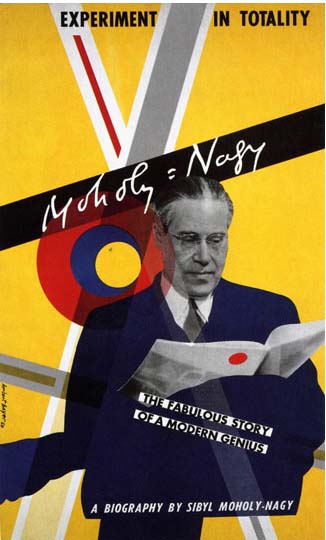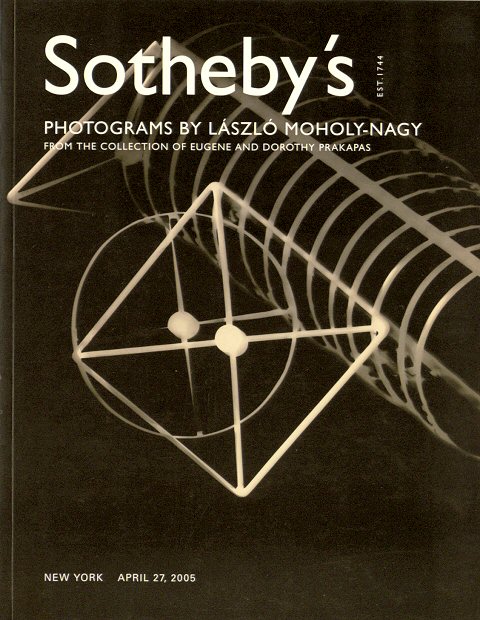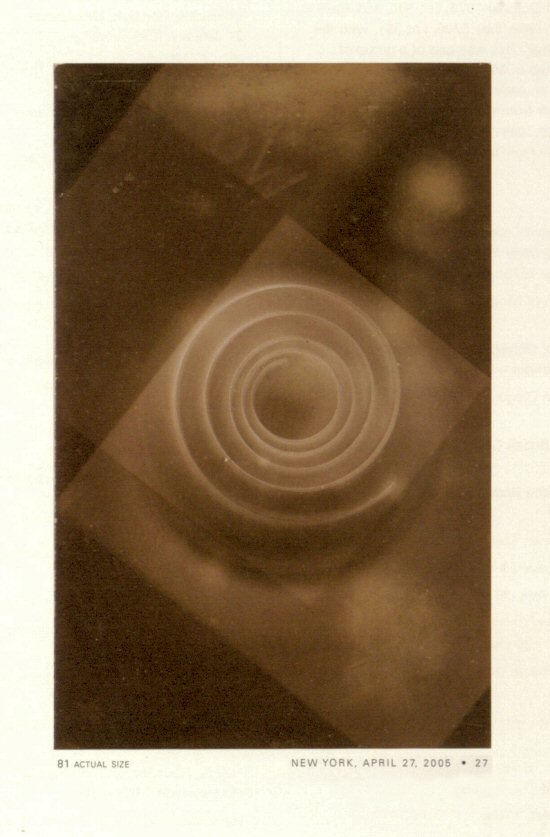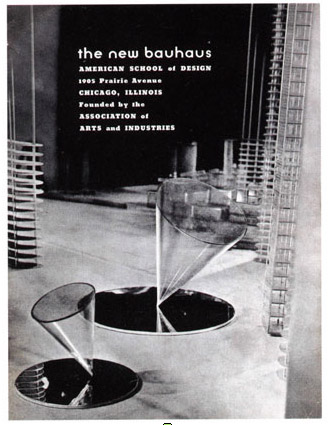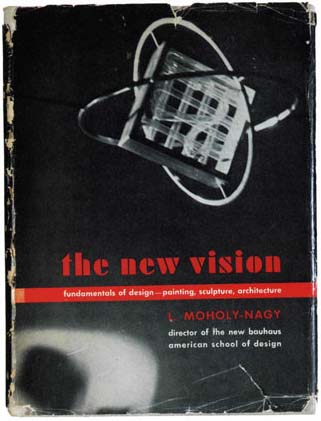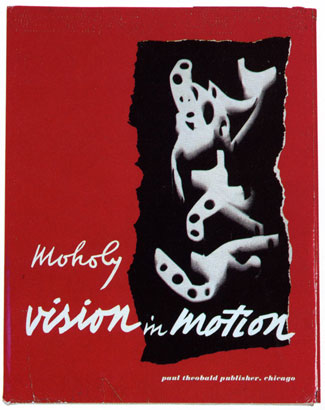
lászló moholy-nagy (1895 1946)Ensaísta, pintor, escultor, desenhador, fotógrafo e autor de fotomontagens, o húngaro Moholy-Nagy foi um verdadeiro «homem renascentista» do séc xx.
A criação de novas relações humanas e artísticas; a tradução da utopia em ação: são esses alguns dos princípios seguidos por Lázló Moholy-Nagy ao longo da sua vasta e diversificada obra.
László Moholy-Nagy (Bácsborsód, Hungria, 20 de Julho de 1895 Chicago, 24 de Novembro de 1946) foi designer, fotógrafo, pintor e professor de design pioneiro, conhecido por ter leccionado na Bauhaus. Foi influenciado pelo Construtivismo Russo e defendeu a integração da tecnologia e indústria no design e nas artes. Para László Moholy-Nagy não existiam divisões entre a fotografia, a pintura, a escultura e a arquitectura. A sua visão global foi fundamental em duas das mais importantes escolas de artes visuais deste século, a Bauhaus e o Chicago Institute of Design. Na Hungria, László ingressou no curso de Direito da Universidade de Budapeste aos 18 anos. Mas a I. Grande Guerra interrompeu os seus estudos no ano seguinte. Foi mandado para a frente, onde seria gravemente ferido. Durante sua convalescença, László dedicou-se aos desenhos e às aquarelas. Mais tarde, com a República Soviética Húngara derrotada, o marxista Moholy-Nagy exilou-se em Berlim, onde entrou em contacto com toda as efervescências culturais do momento, do Futurismo ao Dadaísmo, passando pelo Construtivismo do seu amigo El Lissitzky. Embora na juventude László Moholy-Nagy tenha sido passageiramente influenciado pelo Expressionismo, o artista logo se define como abstracto, influenciado pelo DADA e por Kurt Schwittters: «não penas pela sua sintaxe visual de aglomerações, mas também no imaginário de mecanismos sem sentido». László Moholy-Nagy começou o seu percurso artístico por aderir ao Construtivismo. A sua primeira exposição individual foi realizada em 1922 na galeria Der Sturm, em Berlim. A influência de Malevitch e do Construtivismo russo reflecte-se nas formas geométricas, linha e planos das pinturas de Moholy-Nagy. Bauhaus
A partir de 1923 e até 1928, Moholy-Nagy ensinou e trabalhou na Bauhaus: foi docente na oficina de metal e director do Curso Preliminar (Vorkurs). Começou estas actividades com a idade de 27 anos. A partir de 1923, e em estreita cooperação com Walter Gropius, Moholy-Nagy concebeu e editou a série de livros chamados bauhausbücher. Deste modo, Moholy-Nagy foi um importante impulsionador das actividades editoriais e publicistas da Bauhaus. Casado com a fotógrafa Lucia Moholy, László Moholy-Nagy não demorou a fazer suas primeiras experiências fotográficas. Com uma consistente base teórica, tratou de inovar: na composição, nos pontos de vista, misturando técnicas. Trabalhando na Bauhaus como director da Oficina de metal, Moholy-Nagy continuou produzindo fotos, desenhos, esculturas, e ensaios teóricos. Em 1924, publicou Pintura, Fotografia, Filme, dentro da série de livros que ele editava na Bauhaus. Na Bauhaus, publicou em parceria com Oskar Schlemmer o livro O teatro na Bauhaus, no qual desenvolveu as suas idéias sobre o teatro do futuro.
A nova tipografiaAo longo de toda a sua vida, MN esteve activo no Design gráfico, tendo trabalhado muito com Tipografia e também praticando fotografia e fotomontagem («uma condensação de múltiplas imagens, fixadas num único campo»). Ainda na Hungria, participou na revista Ma (Hoje) , para a qual fez as capas; na Bauhaus, concebeu vários números dos bauhausbücher (livros da Bauhaus); fez também design de publicidade.
Nos seus manifestos, o conceito de uma nova tipografia ocupava um papel central. «die neue typographie» foi o título programático de um artigo de Moholy-Nagy, publicado em 1923 no bauhausbuch, foi um artigo que articulou ideias essenciais da nova tipografia. pouco depois, Jan Tschichold faz ressonância às teses de Moholy-Nagy, ampliando a sua divulgação. Moholy-Nagy, influenciado pelo Neo-plasticismo holandês e pelo Construtivismo russo, substituiu a abordagem expressionista de Johannes Itten. MN considerava a tipografia como um instrumento de comunicação e defendia que: A Tipografia deve comunicar claramente
na forma mais urgente. A claridade deve ser enfatizada [
] A nossa atitude
intelectual perante o mundo é individualmente precisa (essa
precisão está mudando hoje para precisão colectiva, ao
contrario da velha individualidade e das formas amorfas. A influência de Moholy-Nagy na Bauhaus é claramente visível já na campanha publicitária desenvolvida para a grande exposição no verão de 1923. Moholy-Nagy tornou-se praticamente o editor-chefe da Bauhaus, desenhando o layout para o catálogo da exposição, os portfólios e ocupando-se da edição dos bauhausbücher. Com o fecho da Bauhaus na Alemanha, os docentes optam pelo exílio, fugindo às represálias do Nazismo. A evolução continua nos EUA, país para onde tinha emigrado boa parte dos exilados da Bauhaus. László Moholy-Nagy mudou-se para Londres em 1935, e - juntamente com Walter Gropius - rápido se estabeleceu no seio da comunidade vanguardista sedeada nos Lawn Road Flats (London, Hampstead). New Bauhaus
Um grupo de industriais norte-americanos decide fundar em 1937 em Chicago uma escola de Design e chama Moholy-Nagy para dirigi-la. Esta instituição, a New Bauhaus, virá depois a ser designada por School of Design e mais tarde Institute of Design. Estes contextos foram abordados numa grande exposição: "Albers and Moholy-Nagy: From the Bauhaus to the New World". Londres, 2006, na Tate Modern, Bankside, Londres (Reino Unido) biografia / cronologia
Fotografia fotograma fotomontagem«The use of light as a creative agent» Para Moholy-Nagy, a fotografia, os fotogramas e fotomontagens oferecia um novo modo de ver, um novo processo de tornar credível e compreensível a comunicação. Escreveu: «Conhecer a fotografia é tão importante como conhecer o alfabeto. O iletrado do futuro será tanto aquele que ignora a câmara como o que ignora a caneta (...) Cada época tem a sua forma de expressão visual. A nossa: o filme. O signo eclético, simultaneidade na emissão e na recepção de estímulos. Que está na origem de um gradual desenvolvimento de novas bases criativas em vários campos, nomeadamente na tipografia. A tipografia gutenberguiana, que resistiu praticamente até hoje, existe exclusivamente numa dimensão linear. A intervenção do processo fotográfico expandiu-a para uma nova dimensionalidade, reconhecida actualmente como total. O trabalho preliminar neste campo foi feito pelos jornais ilustrados, cartazes e anúncios impressos.» Moholy-Nagy percebeu que a fotografia, nas primeiras décadas do séc. XX, tinha adquirido uma nova função, pela forma e pelo tratamento aos quais podia ser submetida. Mas as potencialidades do meio, da técnica, dos materiais utilizados eram ignorados; assim, nem a pintura era libertada da sua já superada função representativa, nem a fotografia era explorada como meio criativo. Desde o princípio, Moholy-Nagy percebeu que a luz deveria ser considerada um meio, uma construtora da forma. «Com a câmara fotográfica, tornam-se visíveis existências que não poderiam ser percebidas pelo nosso instrumento óptico, o olho.» O movimento, a visão micro ou macroscópica, os raios-x, as inúmeras gradações de cinzentos, as distorções das lentes, as vistas de baixo, de cima, oblíquas... «A câmara fotográfica reproduz a pura imagem óptica, e portanto mostra as verdadeiras distorções e deformações ópticas. Já o olho, associado à experiência intelectual, suplementa os fenómenos ópticos percebidos através de associações, e cria formal e espacialmente uma imagem conceitual. Assim, a câmara pode fornecer as bases para uma visão objectiva.»
Fotogramas, uma invenção de Moholy-NagyO fotograma, para Moholy-Nagy, era a «concretização do fenómeno da luz, que é peculiar ao processo fotográfico e a nenhuma outra invenção tecnológica.». Colocava objectos tridimensionais (opacos, transparentes, sólidos, lisos, texturizados, lineares...) sobre um papel foto-sensível, e a luz que incide sobre os objectos é modulada para criar inúmeros efeitos, contratses e variações de cinzentos. Durante algum tempo, Moholy-Nagy abandonou a fotografia para realizar trabalhos tridimensionais, formas em acrílico, muitas vezes com buracos ou deformações, que deixam passar a luz. Os trabalhos de Moholy-Nagy nesta área dão uma continuidade lógica aos outros trabalhos do artista. Vale citar, em especial, os seus Moduladores de espaço-tempo. Nesta construções cinéticas, exploração os materiais sob a influência na luz. Alguns dos moduladores foram máquinas construídas para o teatro (a light machine for total theater), como produtoras de reflexos da iluminação do ambiente. Também deve ser ressaltado o carácter anti-escultural destas máquinas, na medida em que negam alguns dos valores mais tradicionais da escultura, como por exemplo, massa e volume. cinemaAs preocupações de MN com a luz e o movimento levam-no ao cinema; produz vários filmes, entre os quais o mais conhecido é Light Dislay Black White Grey (1930) a filmagem do Modulador em acção. Nagy tem a preocupação de utilizar o meio como revelação de fenómenos como o som, luz/cor, espaço, forma, movimento, buscando novas relações, em vez da produção de ilusões. teatro«Preocupado com a criação de estruturas ambientais radicalmente diferentes e com a retirada das impurezas externas ao meio teatro, MN concebeu uma performance teatral livre de incumbências literárias, que enfatizaria «formas criativas peculiares apenas ao palco», e «ação de cena total», que ele interpretava como a «activação concentrada de som, luz/cor, espaço, forma e movimento». MN queria antes de tudo destruir as distâncias tradicionais entre os estímulos de comunicação (humanos ou mecânicos) e os espectadores; ele acreditava que estes elementos teatrais, uma vez libertos dos contextos impostos, poderiam ser usados em combinações completamente novas. Ele também reconhecia as possibilidades do uso de diversos materiais e inovações tecnológicas, como filme, automóvel, elevador, aeroplano, assim como outras máquinas e instrumento ópticos, equipamento refletor, etc. Dessas proposições vieram 2 tipos de teatro radical. No primeiro, o Teatro da Totalidade, os actores têm a mesma importância dos outros meios formativos. No segundo, chamado Mechanized Excentric e caracterizado como uma concentração da ação de cena em sua forma mais pura, é o teatro sem nenhum actor ou figura humana, um ambiente de luzes, sons, filmes, odores, música, aparato mecânico (mesmo robots e figurinos mecânicos), e explosões simuladas. Entre os seus trabalhos nesta área, Nagy realizou projectos para Os contos de Hoffman, Madame Butterfly, entre outros trabalhos para teatro e cinema. Um texto de MN sobre o Design, em inglês e português
Designing is not a profession but an attitude László Moholy-Nagy, Vision in Motion, Chicago 1947, p. 42. Design has many connotations. It is the organization of materials and processes in the most productive, economic way, in a harmonious balance of all elements necessary for a certain function. It is not a matter of façade, of mere external appearance; rather it is the essence of products and institutions, penetrating and comprehensive. Designing is a complex and intricate task. It is integration of technological, social and economic requirements, biological necessities, and the psychophysical effects of materials, shape, color, volume, and space: thinking in relationships. The designer must see the periphery as well as the core, the immediate and the ultimate, at least in the biological sense. He must anchor his special job in the complex whole. The designer must be trained not only in the use of materials and various skills, but also in appreciation of organic functions and planning. He must know that design is indivisible, that the internal and external characteristics of a dish, a chair, a table, a machine, painting, sculpture are not to be separated. The idea of design and the profession of the designer has to be transformed from the notion of a specialist function into a generally valid attitude of resourcefulness and inventiveness which allows projects to be seen not in isolation but in relationship with the need of the individual and the community. One cannot simply lift out any subject matter from the complexity of life and try to handle it as an independent unit. There is design in organization of emotional experiences, in family life, in labor relations, in city planning, in working together as civilized human beings. Ultimately all problems of design merge into one great problem: design for life. In a healthy society this design for life will encourage every profession and vocation to play its part since the degree of relatedness in all their work gives to any civilization its quality. This implies that it is desirable that everyone should solve his special task with the wide scope of a true designer with the new urge to integrated relationships. It further implies that there is no hierarchy of the arts, painting photography, music, poetry, sculpture, architecture, nor of any other fields such as industrial design. They are equally valid departures toward the fusion of function and content in design. O design não é uma profissão, é uma atitude. Vision in Motion, 1947. O Design tem muitas conotações. É a organização de materiais e processos do modo mais produtivo e económico, obtendo um equilíbrio harmonioso de todos os elementos necessários para uma determinada função. Não é uma questão de fachada ou de mera aparência externa; é sim a essência tanto de produtos como de instituições, essência penetradora e abrangente. Praticar design é uma tarefa complicada e complexa. Significa integrar requisitos tecnológicos, sociais e económicos, necessidades biológicas e os efeitos psicológicos dos materiais, das formas, das cores, dos volumes e dos espaços: pensando em relações e afinidades. O designer deve saber ver tanto o periférico como o cerne, o imediato e o definitivo, pelo menos no sentido biológico. Deve ancorar o seu trabalho particular num total complexo. O designer deve ser treinado não apenas no uso dos materiais e para obter várias competências, mas também deve ser treinado a apreciar funções orgânicas e o planeamento. Deve saber que o design é indivisível, que as características internas e externas de uma tigela, cadeira, mesa, máquina, pintura ou escultura nunca devem ser separadas. A idéia do design e da profissão de designer como especialista deve ser transformada numa atitude generalista, de uma inventividade tal que permita que os projectos não sejam vistos isoladamente, mas em relação com as necessidades dos indivíduos e da comunidade. Não devemos arrancar qualquer assunto da complexidade da vida, tentando resolvê-lo como uma unidade independente. Existe design na organização das experiências emocionais, na vida familiar, nas relações laborais, no planeamento urbano, no trabalho conjunto de seres humanos civilizados. Ultimamente, todos os problemas do design fundem-se num único grande problema: «o design para a vida». Numa sociedade saudável, esse design para a vida irá encorajar todas as profissões e vocações a contribuírem com a sua parte, já que o grau de inter-relação em todos os trabalhos dá qualidade a qualquer civilização. Isto implica que é desejável que todos resolvam as suas tarefas específicas com a visão ampla de um verdadeiro designer, tendo em mira relações integradas. E também implica a não-existência de hierarquias entre as artes pintura, fotografia, música, poesia, escultura, arquitectura, ou qualquer outra área, como, por exemplo, o desenho industrial. Todos são pontos de partida válidos, rumo à fusão da função e do conteúdo no «design». bibliografiaFIEDLER, Jeannine. Moholy-Nagy. Nova York, Phaidon, 2001. KOSTELANETZ, Richard. Moholy-Nagy. Nova Iorque, Praeger, 1970. MOHOLY-NAGY, Lazlo. Painting, Photography, Film. Cambridge, MIT Press, 1967. MOHOLY-NAGY, Lazlo. Vision in Motion. Chicago, Paul Theobald, 1947. RICHARD, Lionel. Encyclopédie du Bauhaus. Paris, Somogy, 1985. WINGLER, Hans M. The Bauhaus: Weimar, Dessau, Berlin, Chicago. Cambridge, MIT Press, 1969. Catálogo da exposição Bauhaus 50 anos, Buenos Aires 1970.